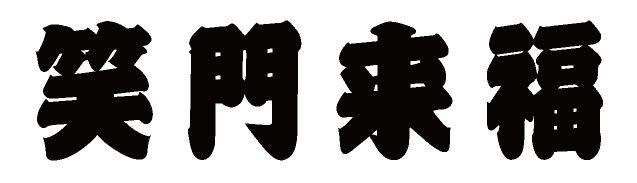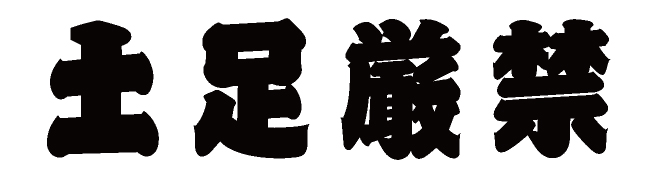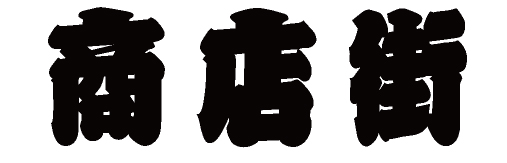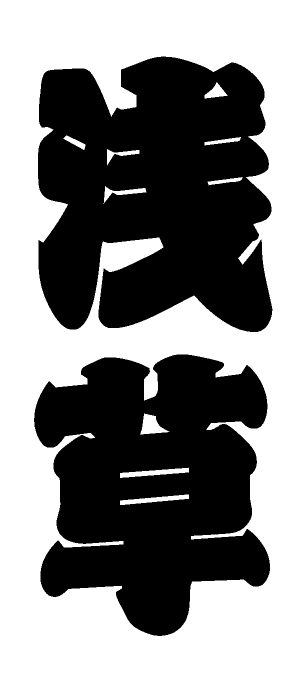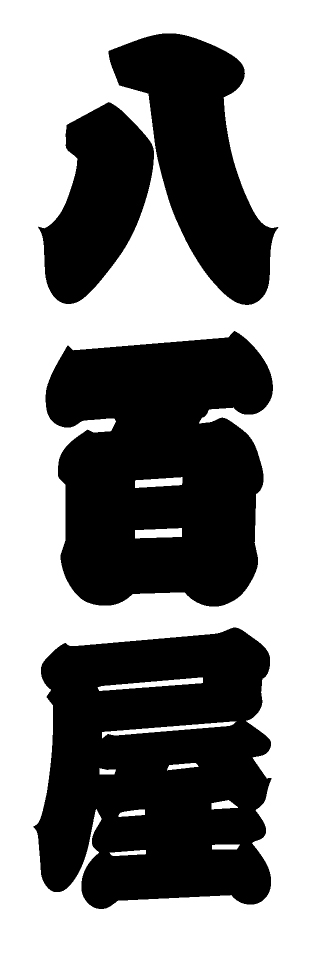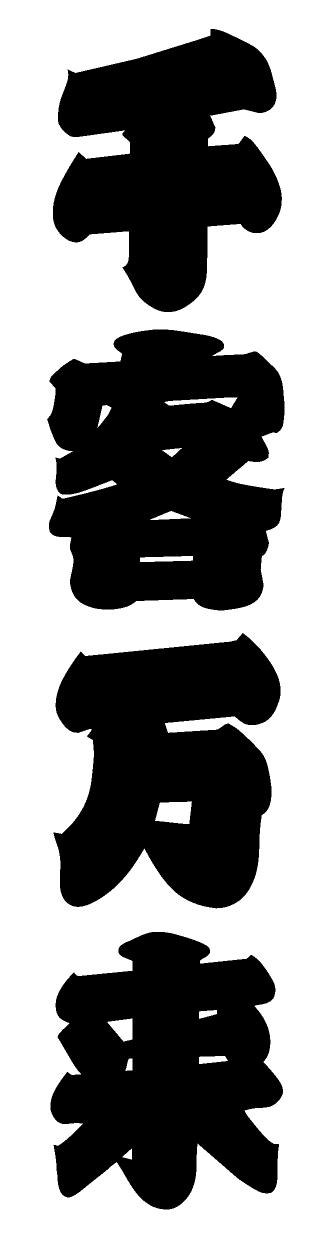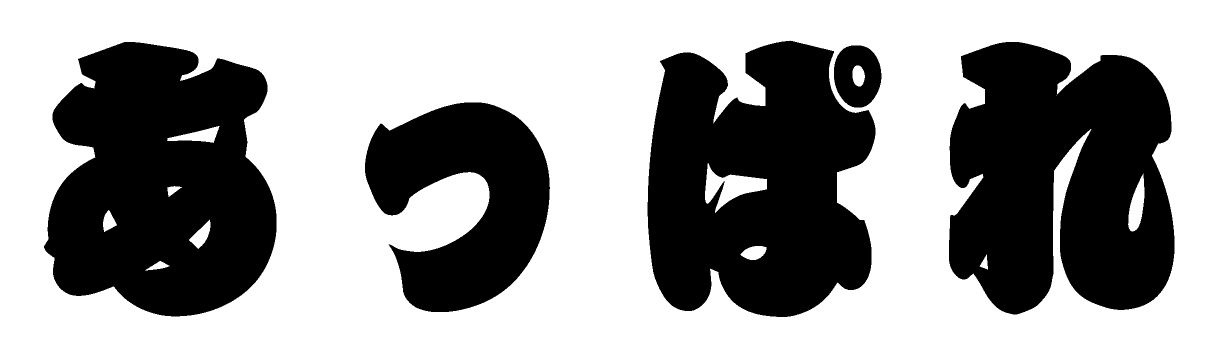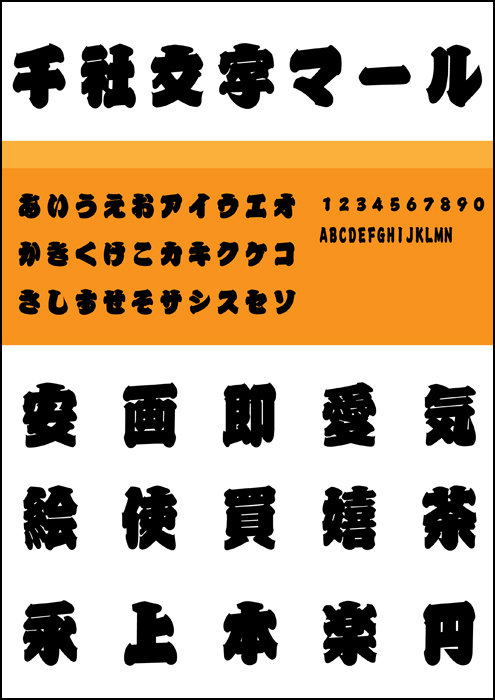
【書:大河原仁】
【概要】
弊社書籍『ディスプレイ書体集 千社文字』(大河原仁 著)をフォント化したものです。この書体は、神社仏閣に多く見られる千社札より取材し、江戸文字のひとつである籠字を母体として生まれました。江戸時代の職人たちは、それぞれに意匠を凝らして、誤字ぎりぎりまでの装飾を文字に施し、互いの「粋」を競い合ってきました。その江戸文字の特徴である、太めの点画と、めりはりのある字形に装飾性を持たせたデザインは、江戸の職人たちの「粋」を損うことなく、現代の文字としての実用性を兼ね備えています。お祭りや年中行事や慶事に最適。フォントフォーマットはTrueTypeです。印刷物への使用など一般的な商業利用は追加料金なしで可能です。詳細については、上記リンク「使用許諾範囲」を、ご購入前に必ずご確認ください。